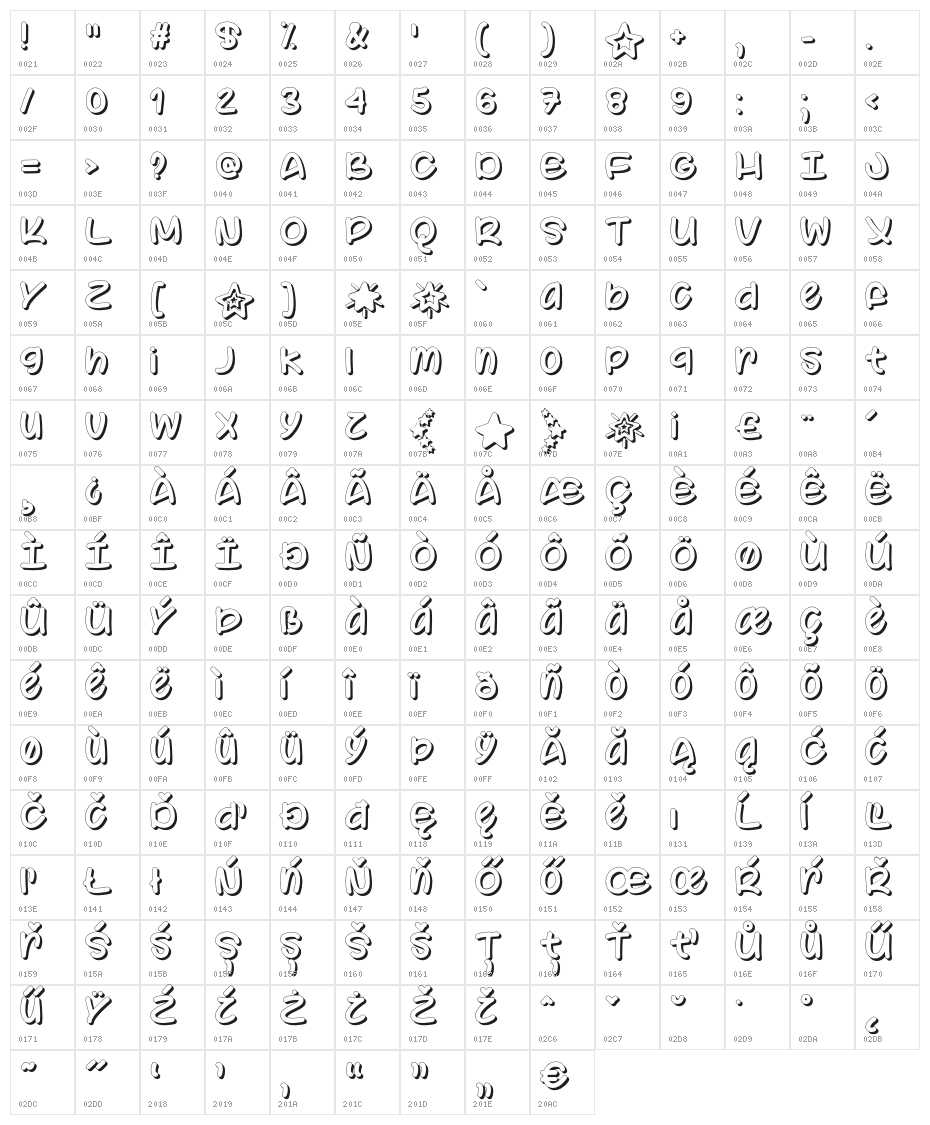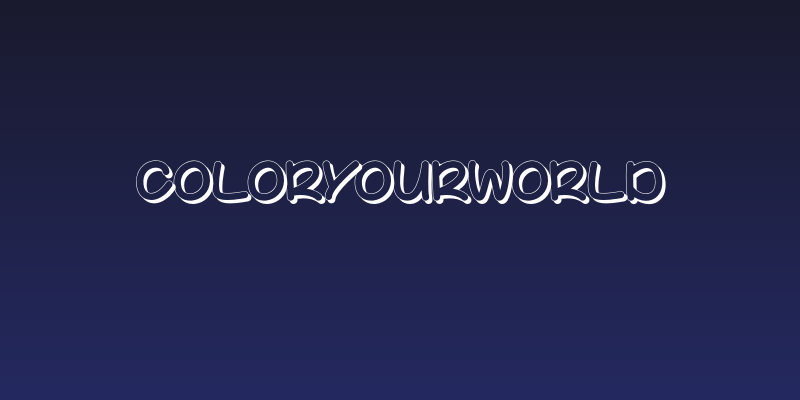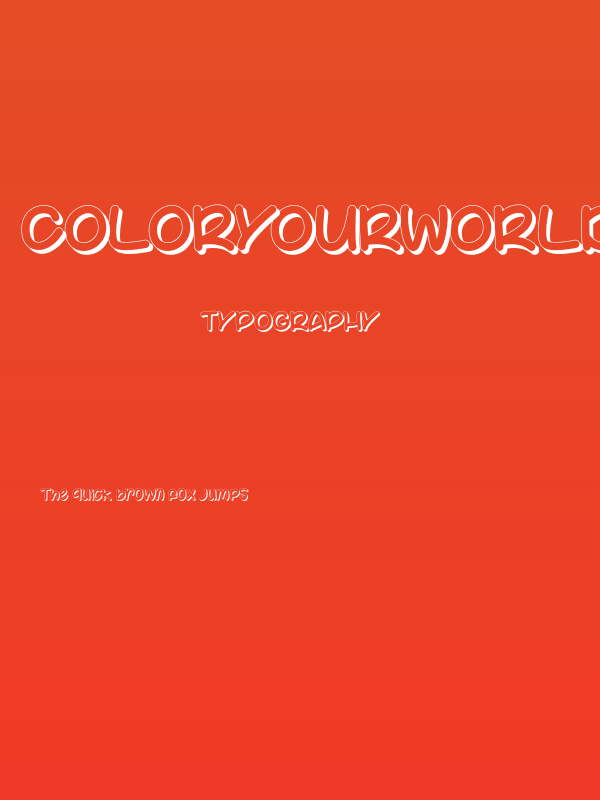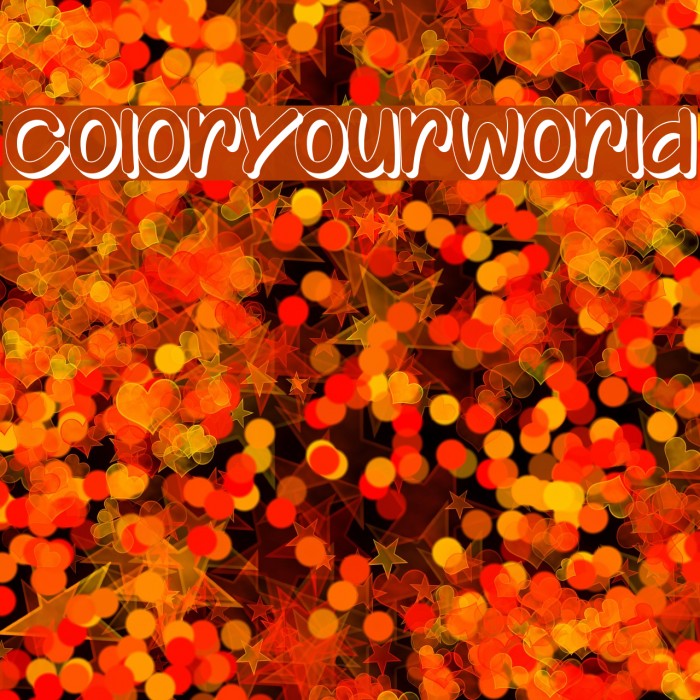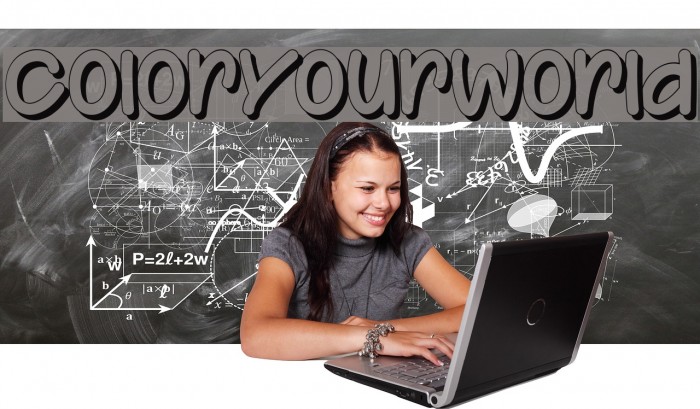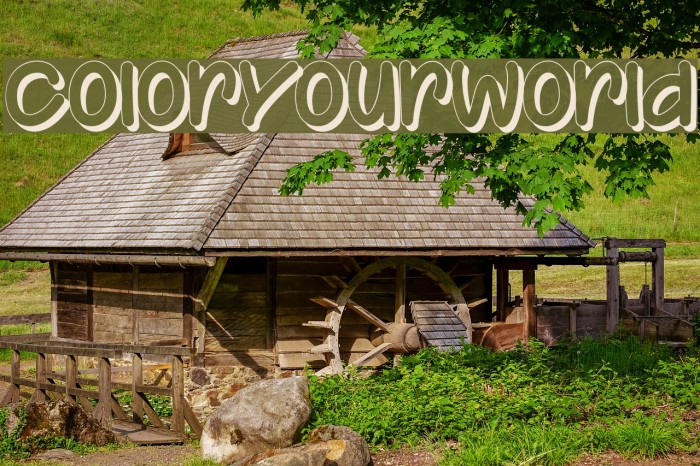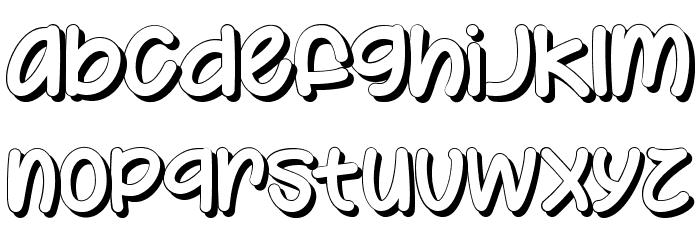
ColorYourWorld Font
| Progetti proposti | Ideal for children's books, party invitations, playful branding, and any project needing a fun, lively touch. |